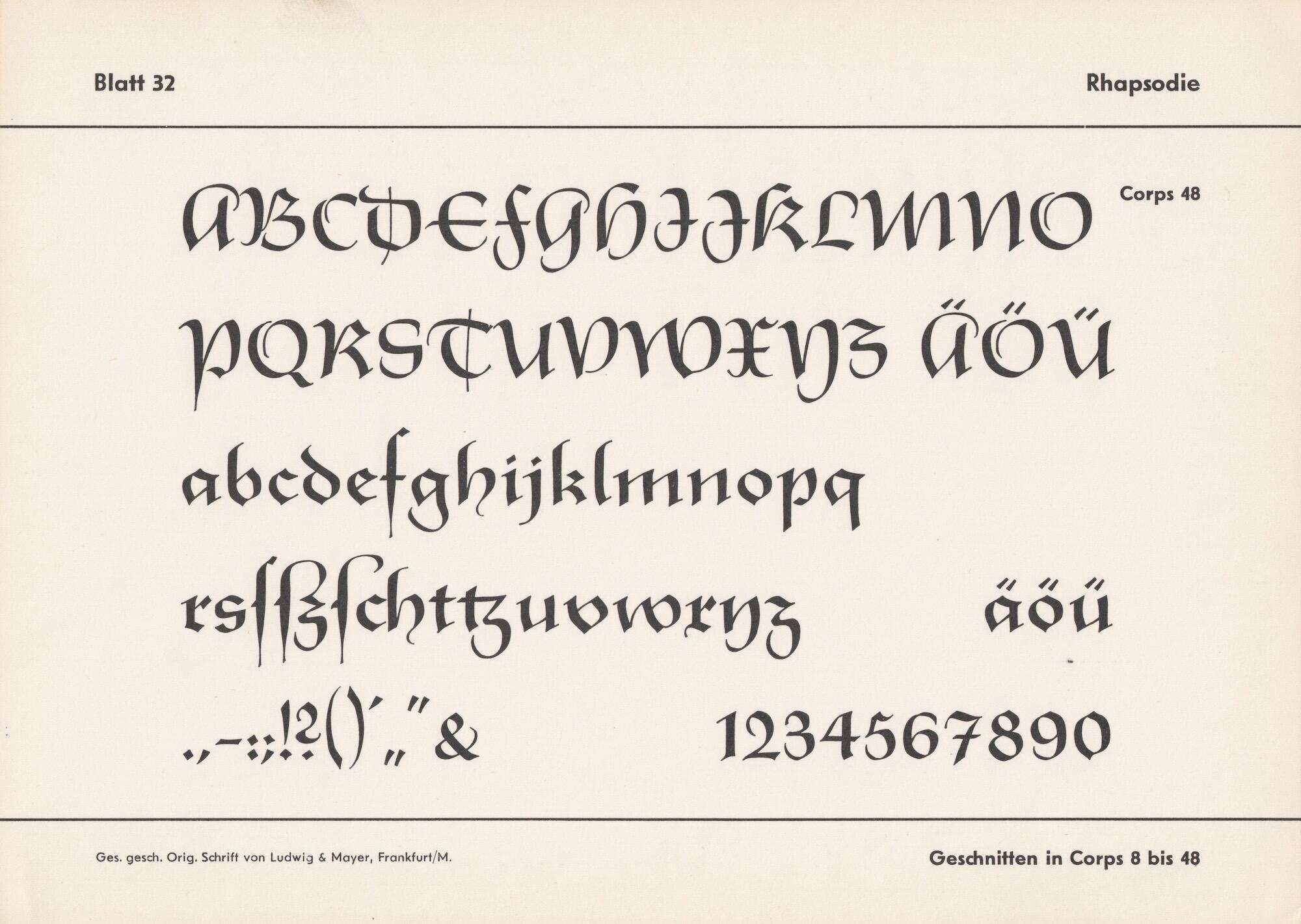
Die Rhapsodie ist eine Bastarda-Schrift von Ilse Schüle und erschien 1951 bei der Schriftgießerei Ludwig & Mayer in Graden von 8 bis 48 Punkt. Zusätzlich erhältlich waren Zierversalien von 16 bis 48 Punkt.
Eine Digitalisierung inklusive der Zierversalien gibt es von Profonts.